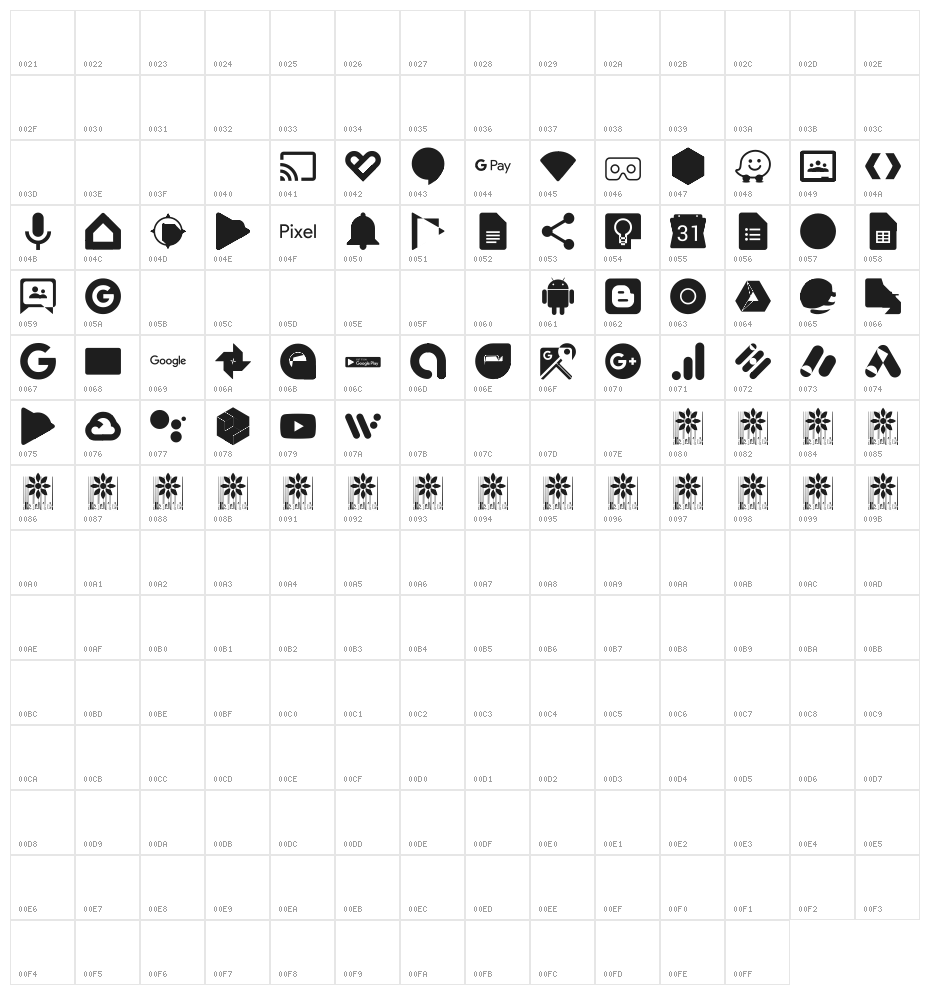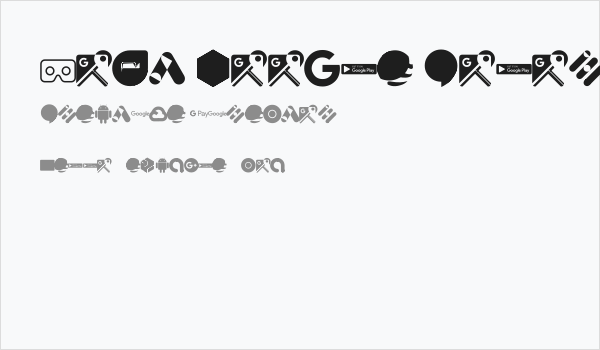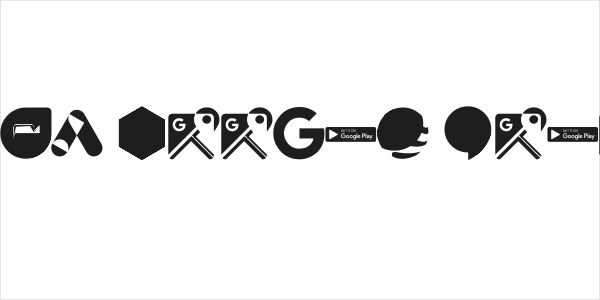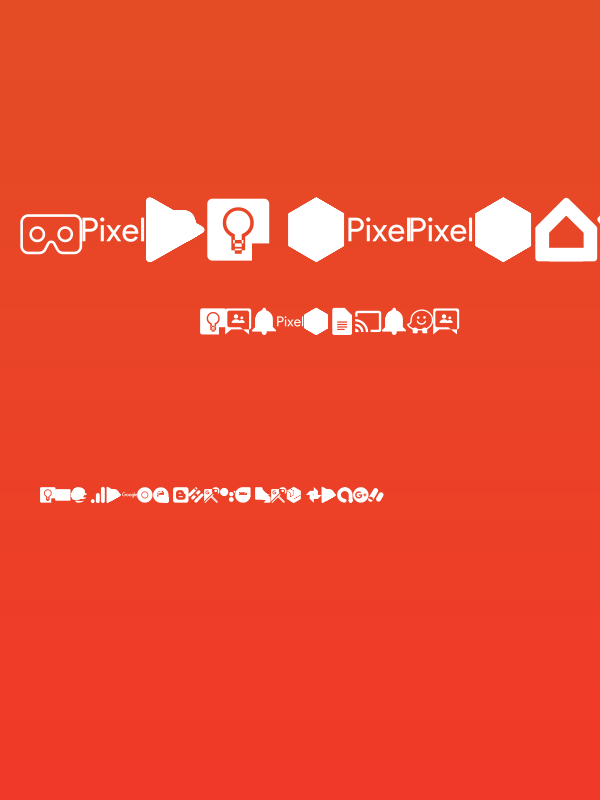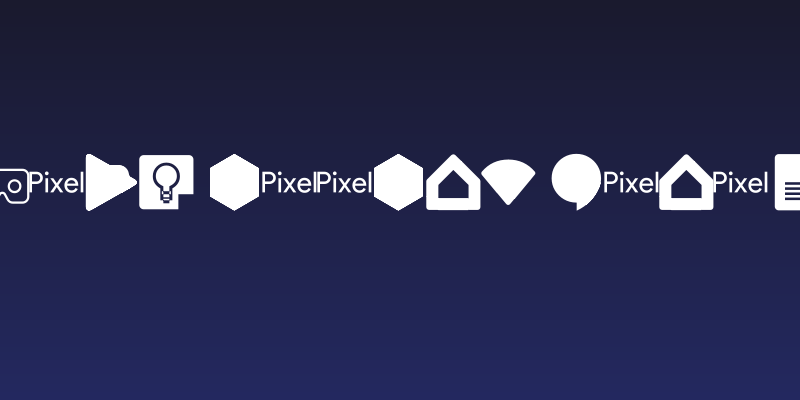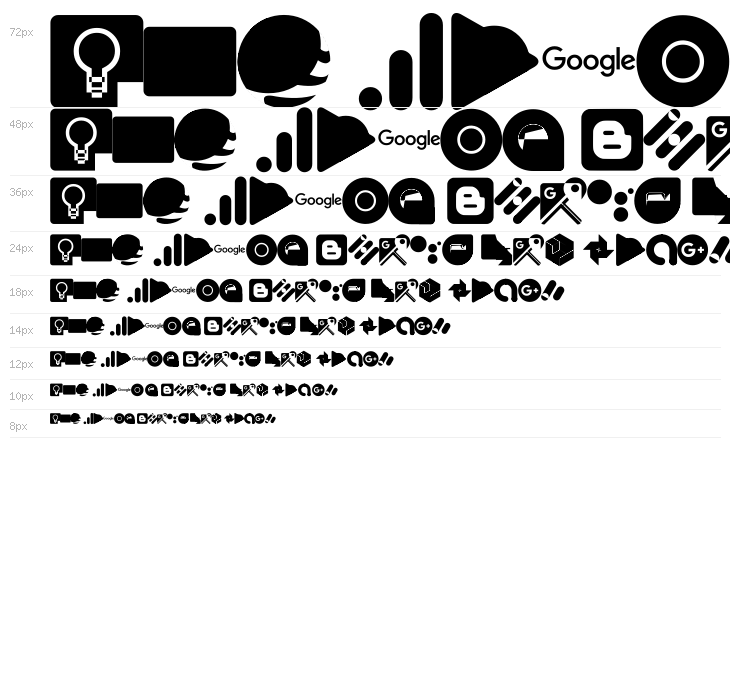
Font Google Color Font
| Gesamtstil | Modern, Minimalist, Tech-oriented |
| Anwendungsfall | Icons, UI elements, branding, app design |
| Vorgeschlagene Projekte | App interfaces, tech branding, UI iconography, digital product design. |